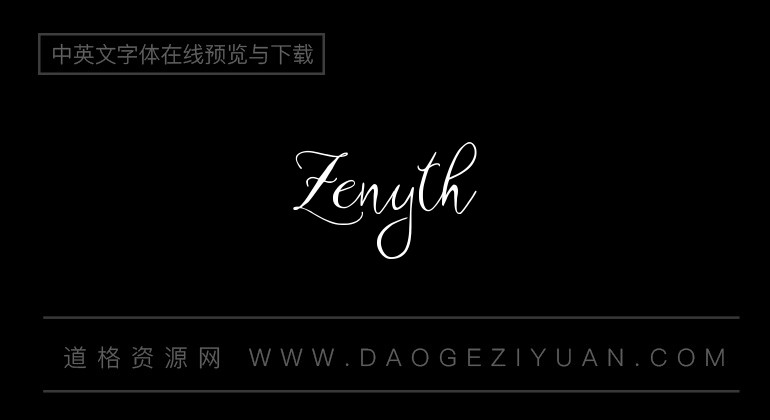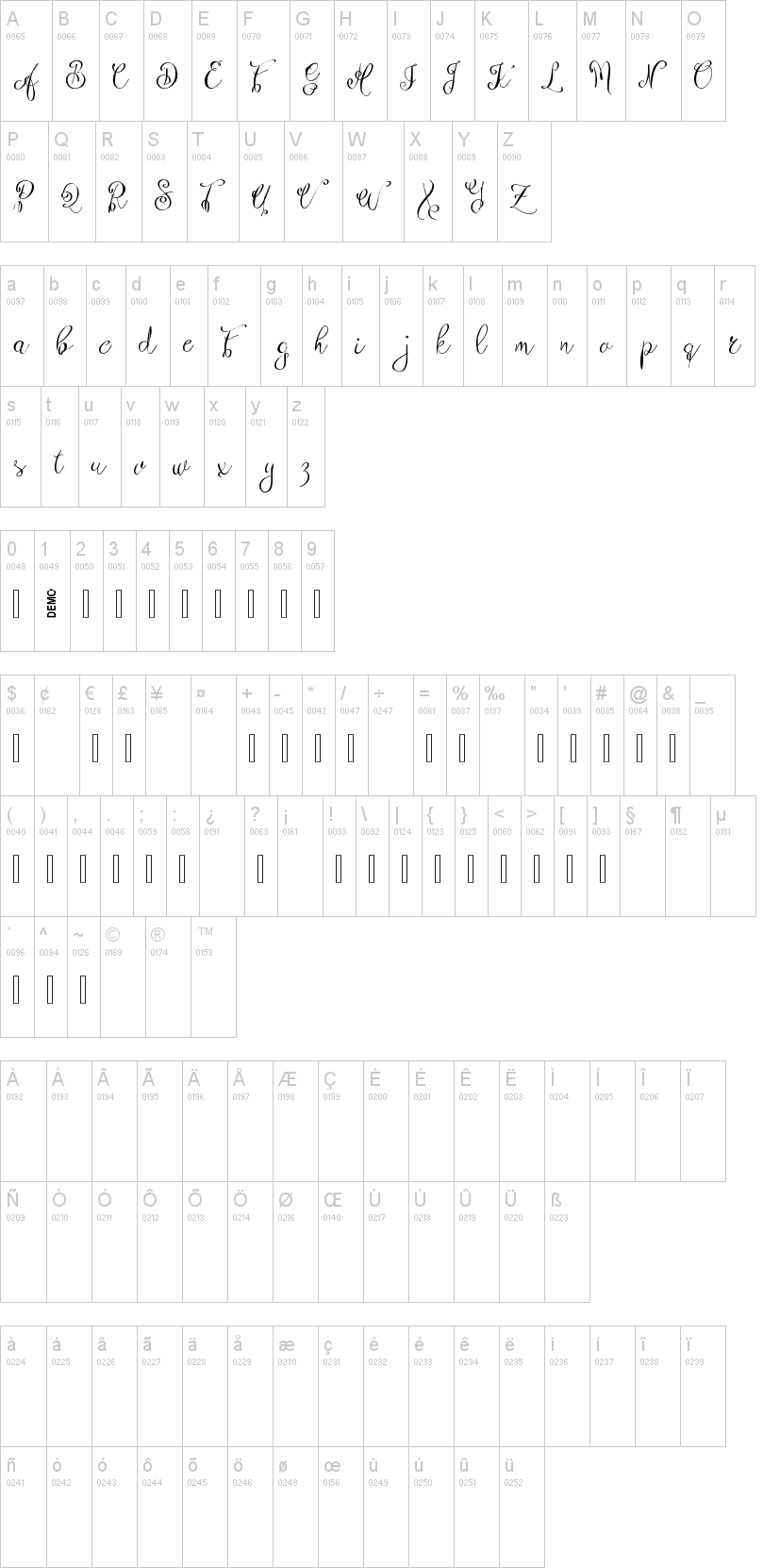
Zenyth 是一种现代、多功能的字体,它由 Monotype Imaging 开发,可以在 Windows 和 Mac 系统上使用。Zenyth 字体有两种风格:细体和粗体,它们都拥有精致的细节和简洁的外观。Zenyth 字体可以用于大多数印刷和网络应用,它的清晰度和可读性都很高,可以满足大多数设计需求。Zenyth 字体也可以用于标题、报头、广告和其他印刷应用,它的简洁外观可以帮助你轻松制作出优雅的设计。内容介绍
Zenyth是一款非常不错的手写艺术字体,具有很好的视觉感,适合于文化类的宣传设计、商业类品牌的广告和产品包装设计以及个性化文字排版等较多场景。